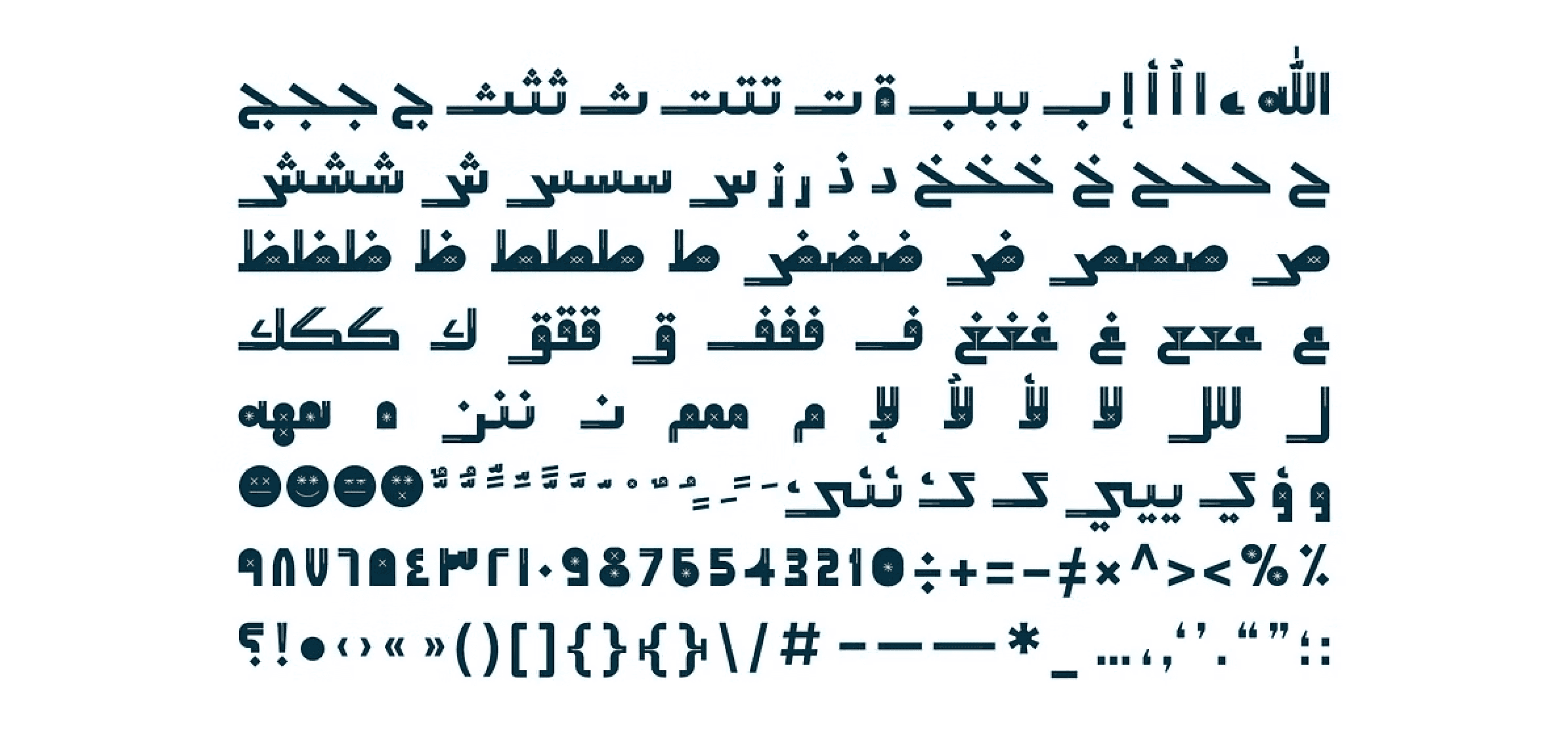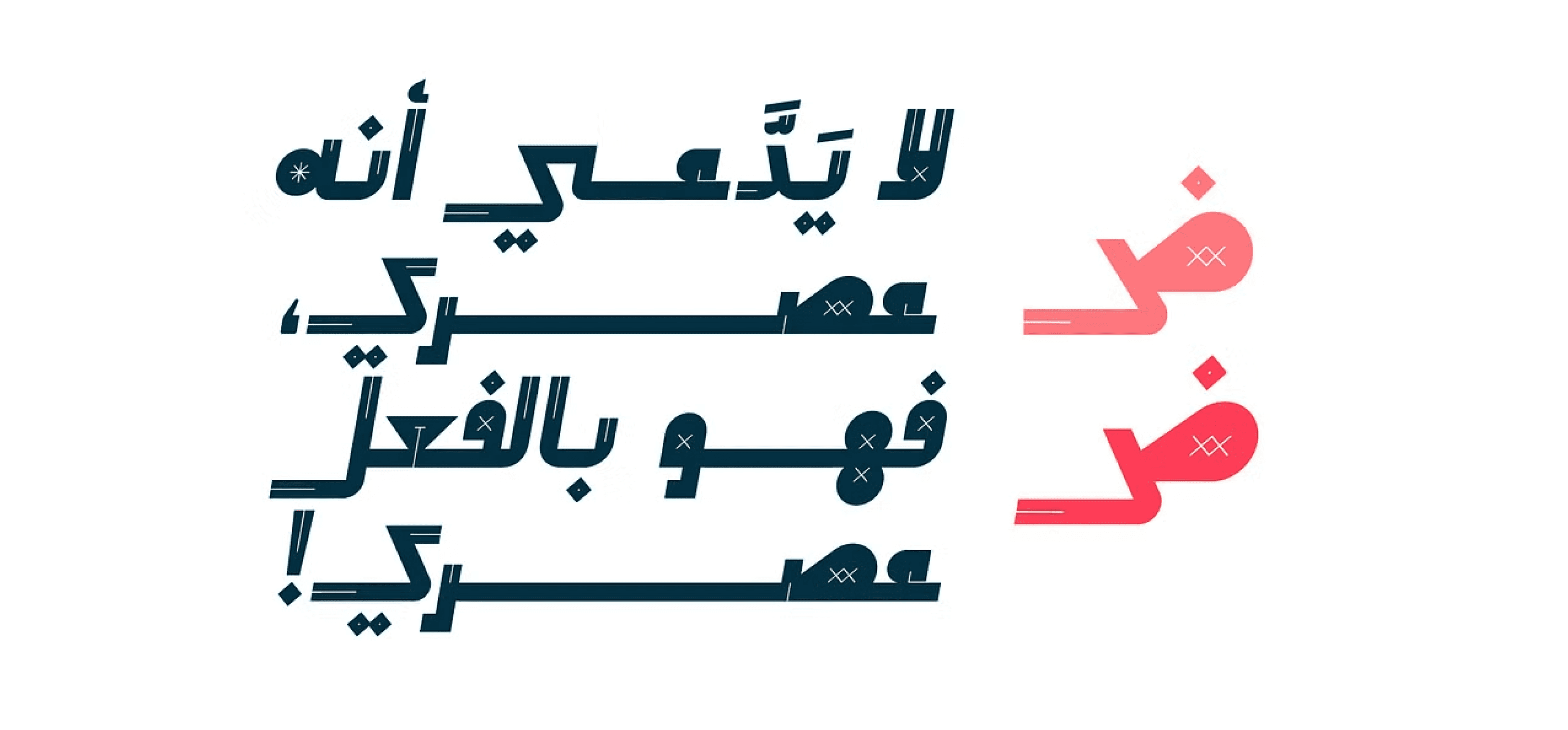
عصري Aasry خط عرض عربي يتميز بتصميم ديناميكي وحاد لأشكال الحروف.
يُعد مناسبًا تمامًا لمشاريع التصميم المعاصر مثل تصميم المواقع، العلامات التجارية، الإعلانات، والطباعة.